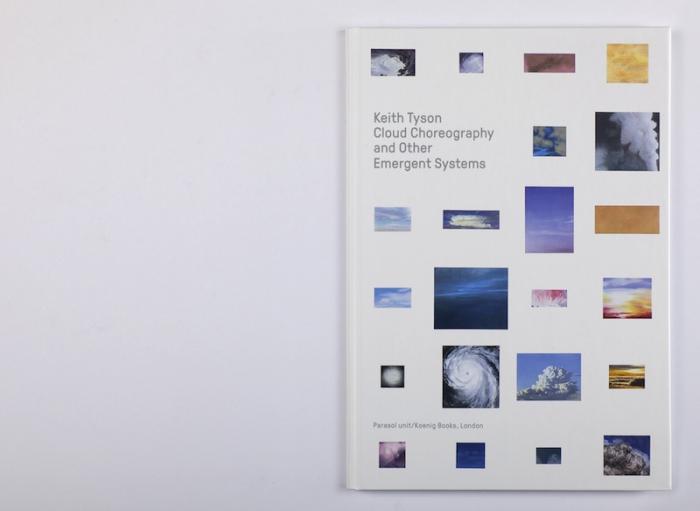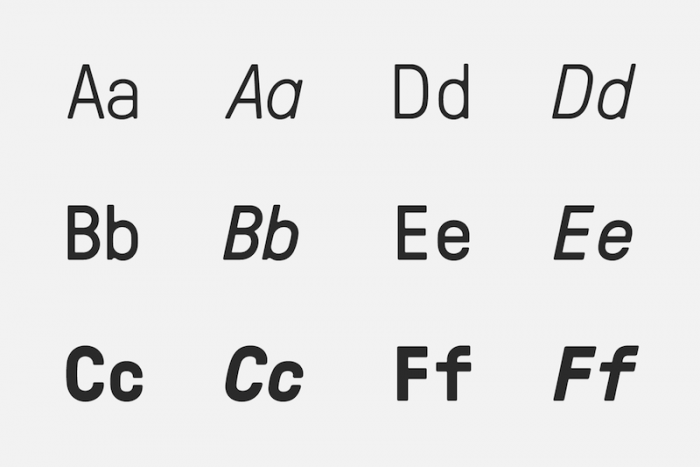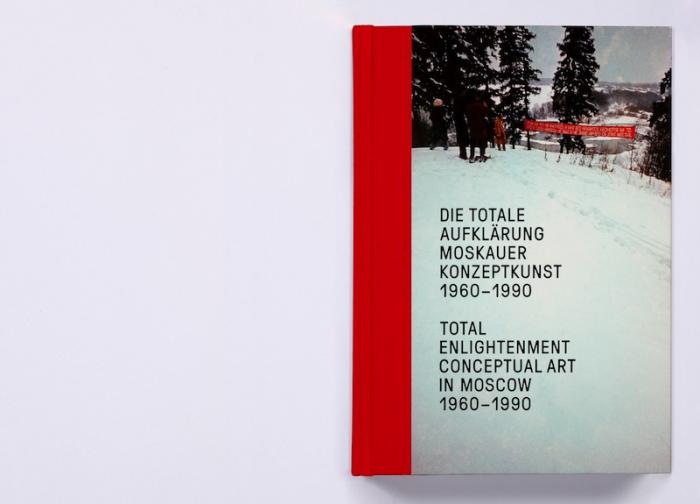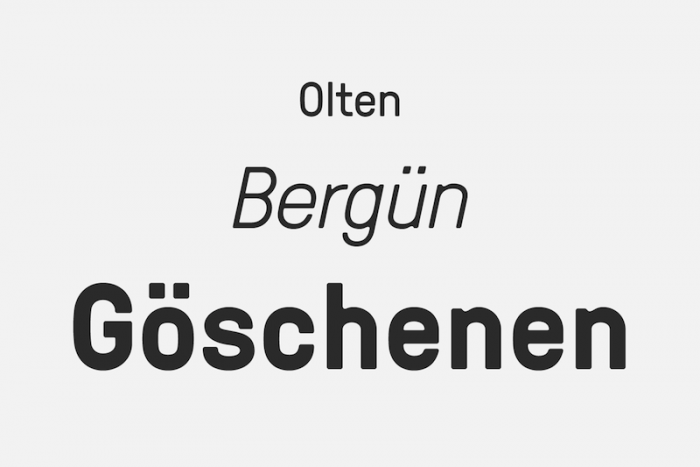
Grilli Type: Neue Website & GT Pressura
Ich freue mich heute unsere neue Webseite sowie unsere neueste Veröffentlichung, GT Pressura, anzukündigen.
Gestaltet von Moiré: Marc Kappeler, Markus Reichenbach with Dominik Huber
Das Design der Pressura ist inspiriert von auf Verpackungen gestampfter Schrift. Die dabei unter Druck zufliessenden Engstellen sind das Markenzeichen dieser Schrift. Die englaufende Serifenlose zeigt dabei Anleihen an wissenschaftliche Beschriftungen, behält aber dank ihrer abgerundeten Ecken eine freundliche Seite. Alle Schnitte sind sowohl in einer proportionalen als auch einer dicktengleichen Version verfügbar.